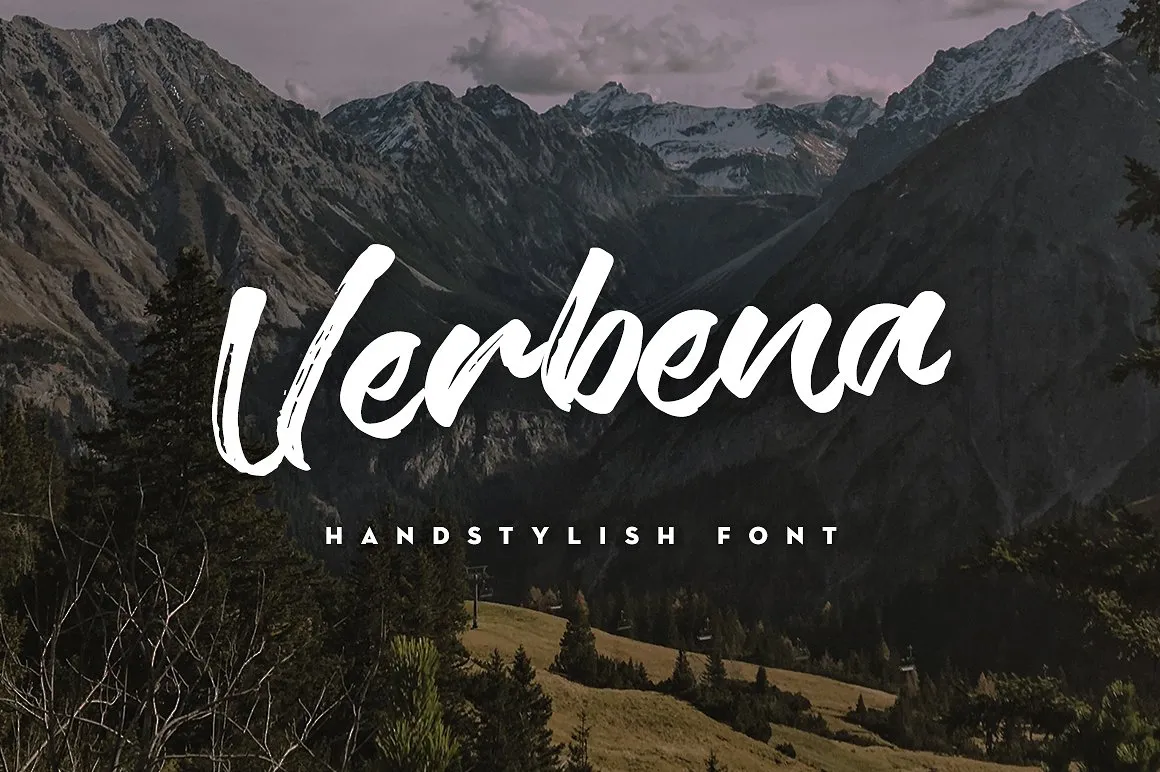
A nova fonte script “Verbena Handstylish Font”, criada pelo designer Alif Devan R., traz uma novidade na categoria das fontes brush. Esta elegante font oferece um visual único e autêntico que é perfeito para a criação de logotipos, cabeçalhos, títulos e outras ideias criativas. Com uma aparência única que remete à arte manual, você pode criar resultados impressionantes simplesmente usando Verbena Handstylish Font! Ideal para qualquer projeto gráfico ou design que busque um toque especial e autêntico, seja ele impresso em papel, digitalizado ou aplicado a outros formatos. Experimente Verbena Handstylish Font e revolucione sua linguagem de design com uma nova abordagem elegante e versátil.